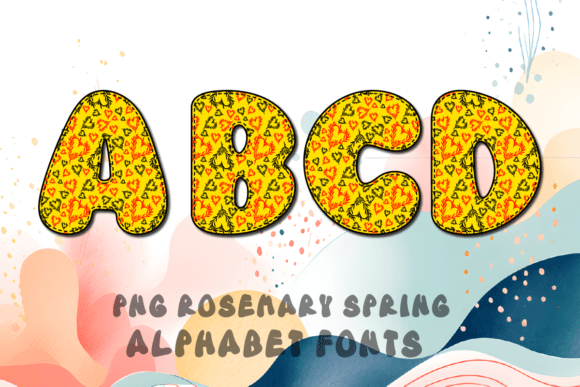
Rosemary Spring Alphabet Fonts
หากคุณกำลังมองหาเนื้อหาคุณภาพสูงเช่น Rosemary Spring Alphabet Fonts แพ็คเกจพรีเมียมนี้เป็นตัวเลือกที่ยอดเยี่ยมสำหรับโปรเจ็กต์สร้างสรรค์ของคุณ
ไม่ว่าคุณจะสร้างผลิตภัณฑ์ POD (Print on Demand) คำเชิญงานแต่งงาน หรือกราฟิกโซเชียลมีเดีย Rosemary Spring Alphabet Fonts ก็เหมาะสมอย่างยิ่ง